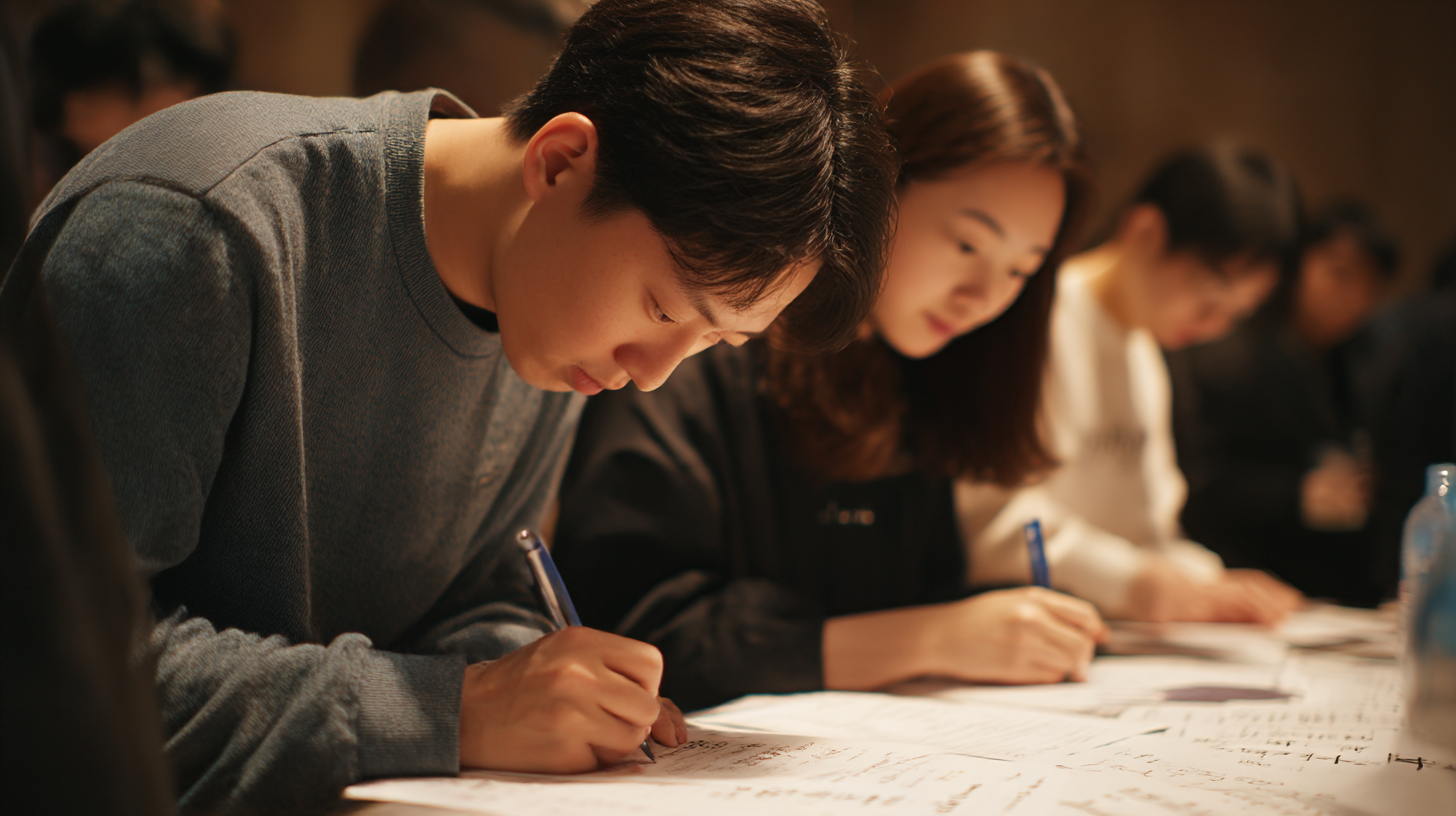
성인도 가능한 바른글씨 교정법 어릴 적에는 반듯하게 글씨를 쓰라고 많이 들었지만, 성인이 된 지금도 내 글씨체가 마음에 들지 않아 고민이 되곤 해요. 특히 회사나 일상에서 손글씨를 써야 할 때, 나도 모르게 나오는 지저분한 글씨는 자신감을 떨어뜨릴 수 있어요. 하지만 너무 걱정하지 않아도 돼요!
성인도 충분히 글씨체를 교정할 수 있고, 하루 5분만 투자해도 큰 변화가 생길 수 있답니다. 지금부터 성인을 위한 바른글씨 교정법을 재미있고 알기 쉽게 소개할게요. ✍💡
이제 본격적으로 글씨체 교정의 세계로 들어가 볼까요? 다음 섹션부터는 정말 실용적인 팁이 가득하니 끝까지 따라와 주세요!
✏ 글씨 교정의 중요성과 필요성
글씨체는 단순한 필기 이상의 의미를 가지고 있어요. 누군가에게는 첫인상을 좌우하는 요소가 되기도 하고, 스스로에게는 표현력과 자존감의 일부가 될 수 있죠. 특히 업무 메모나 감사 카드, 인터뷰 현장 등에서 글씨가 남에게 보여질 때, 깨끗하고 단정한 글씨는 세련된 이미지를 줄 수 있어요.
실제로 한 취업포털의 조사에 따르면, 손글씨가 깔끔한 사람에게 긍정적인 인상을 받는다고 응답한 비율이 70%를 넘었어요. 그만큼 글씨는 무언의 커뮤니케이션 도구로 작용하는 거예요. 내 글씨체가 어지럽거나 휘갈겨진다면, 그 인상도 달라질 수 있다는 거죠.
이런 점에서 볼 때 성인에게도 글씨 교정은 충분히 의미 있어요. 어릴 적 훈련이 부족했거나, 컴퓨터에 익숙해져 손글씨가 줄어든 이들에게는 오히려 지금이 좋은 기회일 수 있어요. 글씨는 연습을 통해 얼마든지 바뀔 수 있거든요!
내가 생각했을 때 글씨 교정은 단순히 ‘예쁘게 쓰기’를 넘어서 집중력, 자존감, 표현력까지 키울 수 있는 좋은 방법 같아요. 글씨가 바뀌면 내 태도와 마음가짐도 긍정적으로 달라질 수 있어요.
📊 글씨체가 주는 첫인상 조사 결과
항목 긍정 응답률 부정 응답률 비고 깔끔한 손글씨 71% 12% 호감도 높음 흘려쓴 글씨 15% 64% 신뢰도 낮음 필기체 스타일 36% 28% 개성 표현 가능 이처럼 글씨는 단순한 기록이 아니라, 나를 표현하는 중요한 요소예요. 다음 섹션에서는 좋은 글씨를 쓰기 위한 첫걸음, ‘자세’에 대해 알아볼게요.🧘
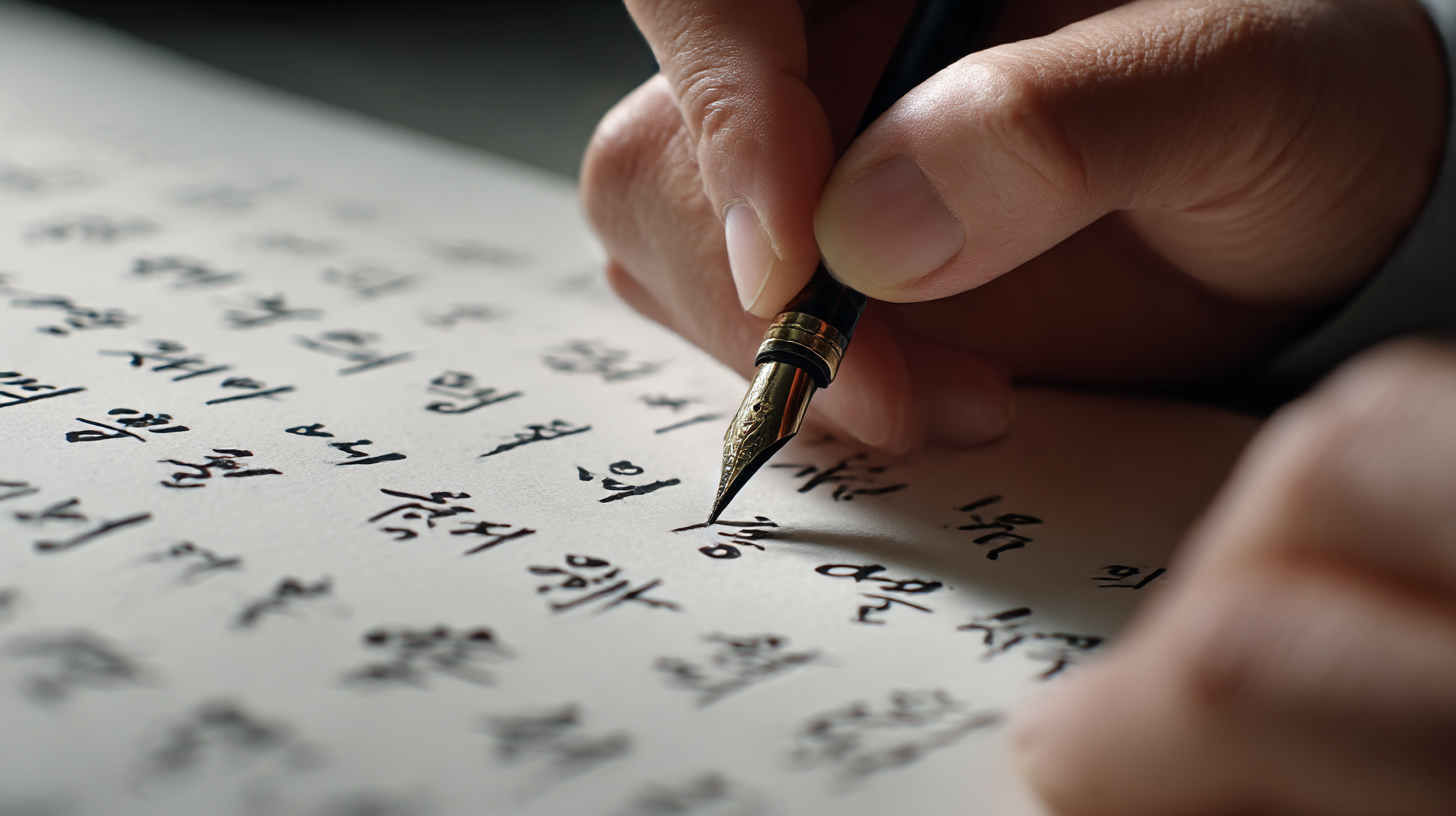
글씨 교정의 중요성과 필요성 🧘 올바른 자세가 주는 효과
글씨체를 바꾸고 싶다면 가장 먼저 바꿔야 할 건 바로 '자세'예요. 글씨는 손으로 쓰지만, 그 기반은 몸 전체의 균형에서 시작되거든요. 특히 등과 어깨가 구부정하거나, 고개가 너무 숙여진 상태에서는 손끝의 움직임도 자연스럽지 않게 돼요.
좋은 자세는 글씨를 또렷하게 만들 뿐 아니라, 오래 써도 손에 무리가 덜 가게 도와줘요. 책상과 의자 높이가 잘 맞지 않으면 글씨체가 삐뚤어지고, 손목이나 팔에도 피로가 쉽게 쌓이게 되죠. 그래서 ‘앉는 법’부터 제대로 익히는 게 중요해요!
올바른 자세의 핵심은 3가지예요: 허리를 곧게 펴고, 팔꿈치는 책상에 붙이며, 눈과 노트의 거리는 30cm 이상 유지하기! 간단하지만 이 기본만 잘 지켜도 글씨의 선이 훨씬 안정감 있어져요. 특히 눈과의 거리 조절은 시력 보호에도 좋답니다. 👀
몸의 중심을 잡는 연습은 명상이나 요가에서도 중요하게 여겨지죠. 글씨체 교정에서도 자세가 바로 중심축이 되어줘요. 중심이 흔들리면 글씨도 흔들리는 법이니까요. 글씨 교정을 위한 첫걸음은 바른 자세부터 시작해요! 💺
📋 바른 글씨 자세 체크리스트
자세 항목 좋은 습관 피해야 할 습관 허리 자세 의자 등받이에 바르게 기대기 허리를 앞으로 구부정하게 굽힘 팔의 위치 팔꿈치를 책상에 고정 팔을 공중에 띄운 채 쓰기 시선 거리 눈과 종이 사이 30~35cm 고개를 너무 숙이거나 가까이 붙이기 좋은 글씨를 위한 몸의 준비가 끝났다면, 이제 실전으로 들어가야겠죠? 다음 섹션에서는 하루 5분만 투자해도 되는 실천 가능한 글씨 교정법을 알려줄게요! 🕐✍
🕐 하루 5분, 실천 가능한 교정법
글씨 교정이라고 하면 거창한 연습장을 사고 매일 몇 시간씩 해야 할 것 같지만, 사실 매일 딱 5분만 꾸준히 해도 놀라운 변화가 생겨요. 중요한 건 '짧고 정확하게', 그리고 '지속적으로' 하는 거예요. 이건 글씨뿐만 아니라 모든 습관 형성의 기본이기도 하죠.
우선 추천하고 싶은 첫 번째 방법은 ‘베이스라인 연습’이에요. 이는 글씨를 쓸 때 기준이 되는 선에 맞춰 일정한 크기와 간격으로 쓰는 훈련이죠. 낙서처럼 쓰던 글씨도 베이스라인을 의식하며 쓰면 한결 정돈된 느낌을 줄 수 있어요.
두 번째는 ‘느리게 쓰기’예요. 평소보다 두 배 느린 속도로 한 자 한 자를 의식하면서 써보세요. 처음엔 답답할 수 있지만, 이 과정에서 글자의 균형과 모양을 자연스럽게 익힐 수 있어요. 특히 자주 틀리는 글자나 모양이 이상한 글자는 반복 연습이 효과적이죠.
세 번째는 ‘거울 보고 쓰기’예요. 이건 거울에 비친 글씨를 보면서 구조적 불균형을 확인하고, 교정하는 훈련이에요. 약간 생소하게 느껴질 수 있지만, 의외로 효과가 좋아서 필기체 연습에도 많이 활용된답니다. 🎯
🗂 하루 5분 훈련 루틴 예시
시간 훈련 내용 목표 효과 1분 손 풀기, 스트레칭 손목 유연성 확보 2분 베이스라인 연습 글자 정렬과 균형 1분 느리게 필기 자세 교정 및 집중력 향상 1분 거울 연습 글씨체 자가 점검 하루 5분만 투자하면 부담도 없고, 오히려 짧은 시간이라 더 집중해서 할 수 있어요. 중요한 건 “내일도, 모레도 하자”는 마음가짐이에요. 이제 글씨 교정을 도와주는 도구들에 대해 소개할게요. ✏
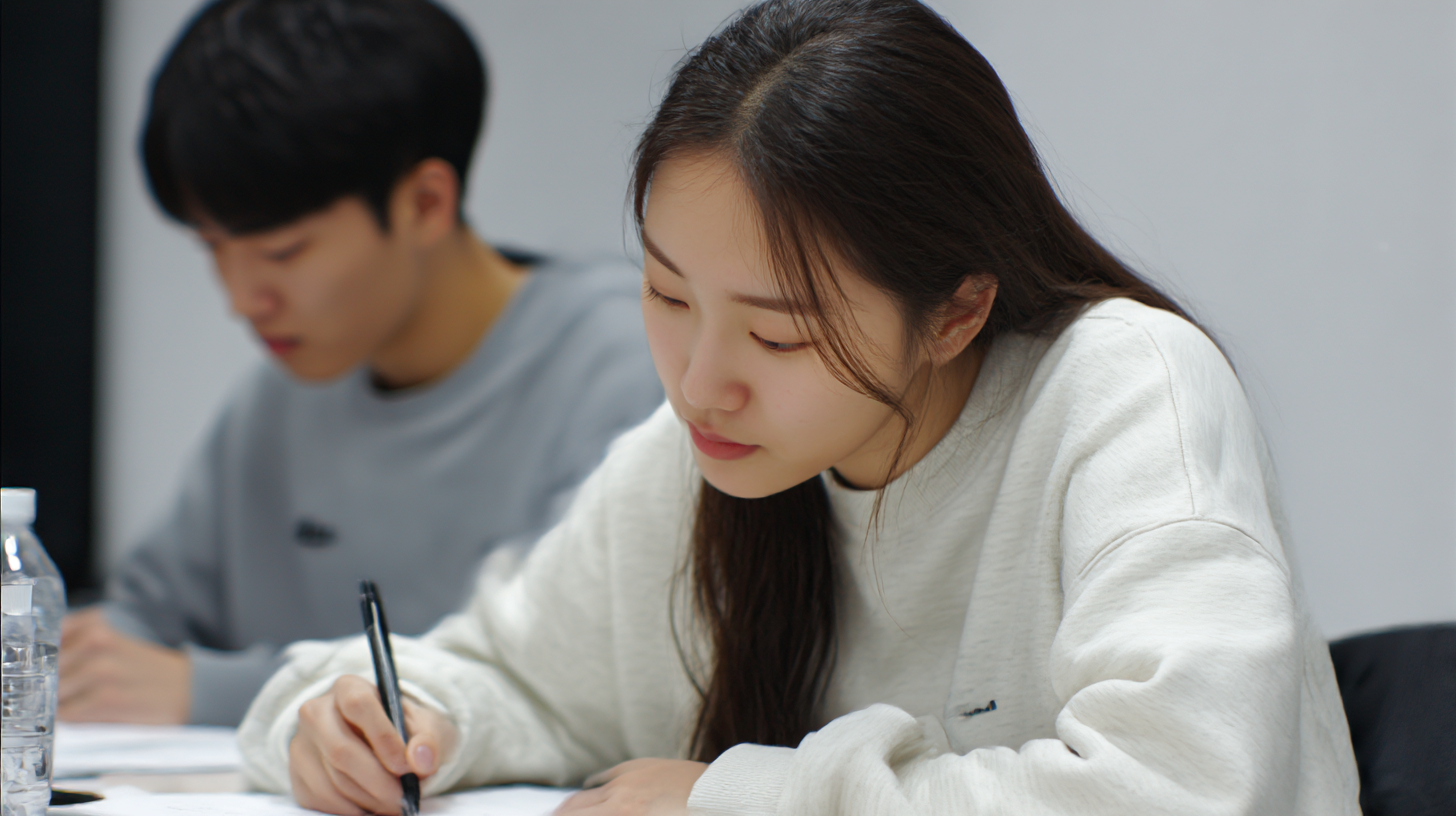
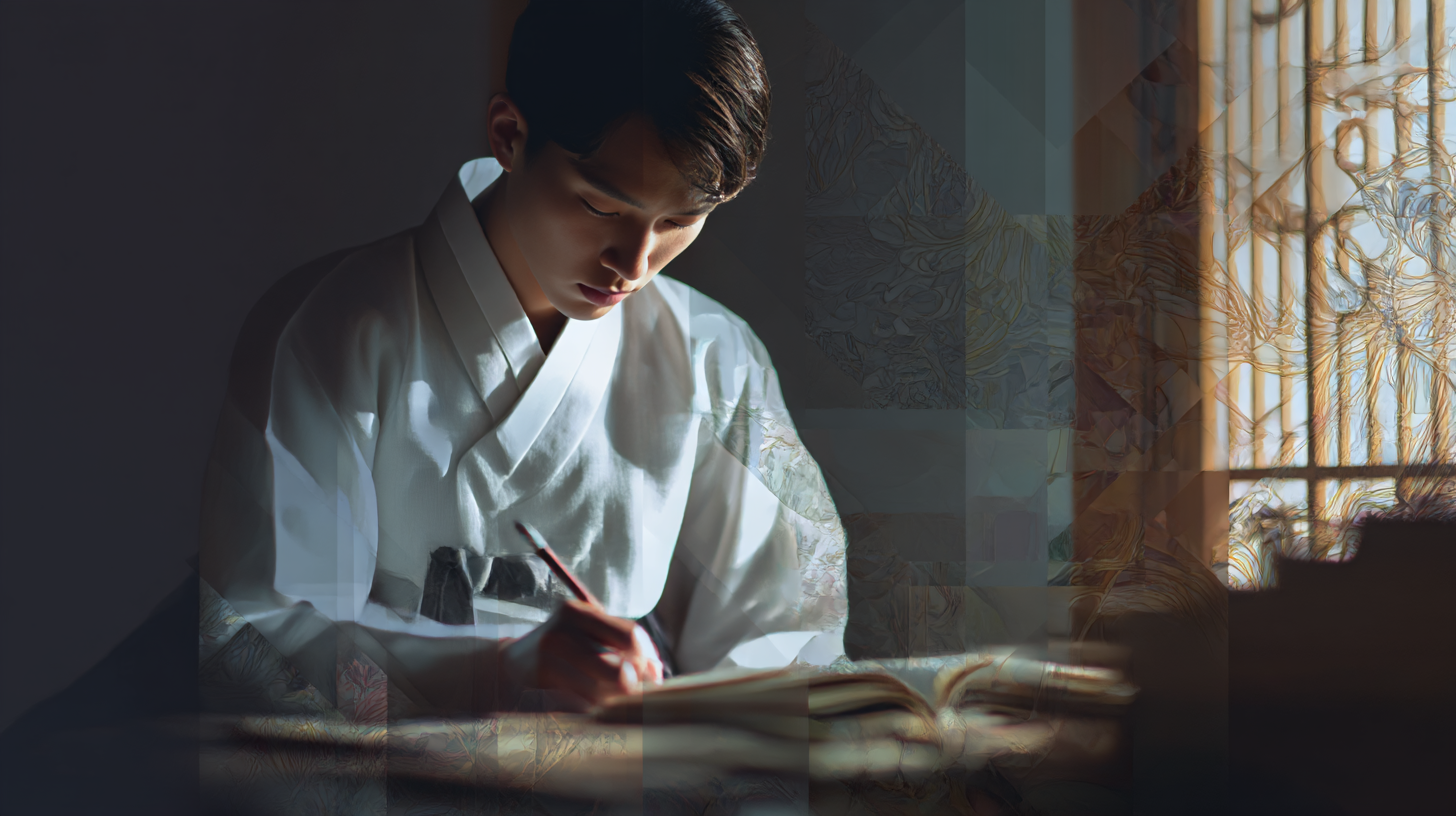
하루 5분, 실천 가능한 교정법 🖊 도움이 되는 필기 도구 추천
글씨체 교정에서 필기 도구는 생각보다 큰 역할을 해요. 손에 잘 맞지 않는 펜이나 종이를 쓰면 필기감이 불편하고, 그만큼 글씨도 부정확해지거든요. 그래서 연습할 땐 내 손에 꼭 맞는 도구를 고르는 게 아주 중요해요.
먼저 펜부터 이야기해 볼게요. 초보자라면 잉크 흐름이 일정한 젤펜이 좋아요. 너무 미끄럽지 않으면서도 부드럽게 써지기 때문에 선의 굵기를 조절하기 쉽고, 힘 조절도 자연스러워요. 샤프나 볼펜도 괜찮지만, 펜촉이 얇아 지나치게 긴장되면 손이 떨리기 쉬워요.
노트도 중요해요. 줄이 없는 백지보다는 연습용 유선지, 특히 ‘세로 8mm 라인’이 있는 공책이 좋아요. 이 줄 간격은 한글의 구조에 맞춰져 있어서 정자체 연습에 최적화되어 있답니다. 그리고 종이 재질도 부드럽고 번짐 없는 것이 좋아요.
마지막으로, 펜을 잡는 ‘그립 보조기’도 추천해요. 펜을 바르게 잡는 훈련을 도와주기 때문에 손가락 위치가 안정되면서 글씨도 더 정돈돼 보여요. 특히 성인 중에도 펜을 잘못 잡는 경우가 많아, 초기엔 이런 도구들이 큰 도움이 돼요.
🖍 글씨체 교정에 추천하는 도구들
도구명 특징 추천 이유 제브라 사라사 젤펜 잉크 흐름이 부드럽고 고르게 나옴 초보자도 손쉽게 정자체 가능 8mm 유선 노트 가이드라인이 있어 글씨 정렬에 도움 형태 안정성 향상 실리콘 그립 보조기 펜 잡는 위치 교정 가능 올바른 필기 습관 형성에 효과적 좋은 도구는 연습을 더 쉽게, 더 즐겁게 만들어줘요. 부담 없이 쓰기 좋고 꾸준히 연습할 수 있는 도구들을 잘 선택해서 시작해 보세요. 다음 섹션에서는 이 연습을 습관으로 만드는 방법을 알려줄게요! 🗓
📆 꾸준함을 위한 습관 만들기
좋은 글씨체를 만드는 핵심은 바로 ‘꾸준함’이에요. 하루 5분이 아무리 짧아도, 그 5분이 매일 이어진다면 글씨는 확실히 달라져요. 실제로 많은 사람들이 ‘하루 5분 루틴’을 30일만 실천해도 눈에 띄는 차이를 경험한다고 해요.
습관을 만드는 가장 쉬운 방법은 ‘정해진 시간에 같은 장소에서 하기’예요. 예를 들어, 아침에 커피 마시기 전에 5분간 연습하거나, 자기 전 5분을 정자체 쓰기로 정해보세요. 반복은 뇌에 ‘이건 일상이다’라는 신호를 주게 되죠.
또한 눈에 보이는 변화가 있어야 동기부여가 되니까, 연습한 글씨를 매일 사진으로 남겨보세요. 일주일, 한 달 뒤 비교해보면 스스로도 놀라게 될 거예요. SNS에 올려 다른 사람들과 공유하는 것도 좋고요. 🔄📸
그리고 작은 성공을 자주 느끼는 것도 중요해요. 예를 들어, 한 줄만 예쁘게 쓰기, 10분 동안 집중하기 같은 미션을 달성했을 때 스스로에게 ‘잘했어!’라고 말해주는 거죠. 습관은 이런 긍정적 피드백과 함께 자라나요. 🌱
📈 글씨 연습 꾸준함 실천법
방법 내용 효과 시간 고정 하루 중 정해진 시간에 연습 루틴 형성 쉬움 시각화 전후 비교 사진 기록 진행 상황 파악 보상 시스템 작은 목표 후 보상 동기부여 상승 이제 어느 정도 글씨 교정의 방법과 도구, 그리고 꾸준함까지 익혔다면… 실제로 이 방법을 실천해서 바뀐 사람들이 있을까요? 물론이죠! 다음 섹션에서는 직접 교정에 성공한 분들의 후기를 소개할게요. 💬
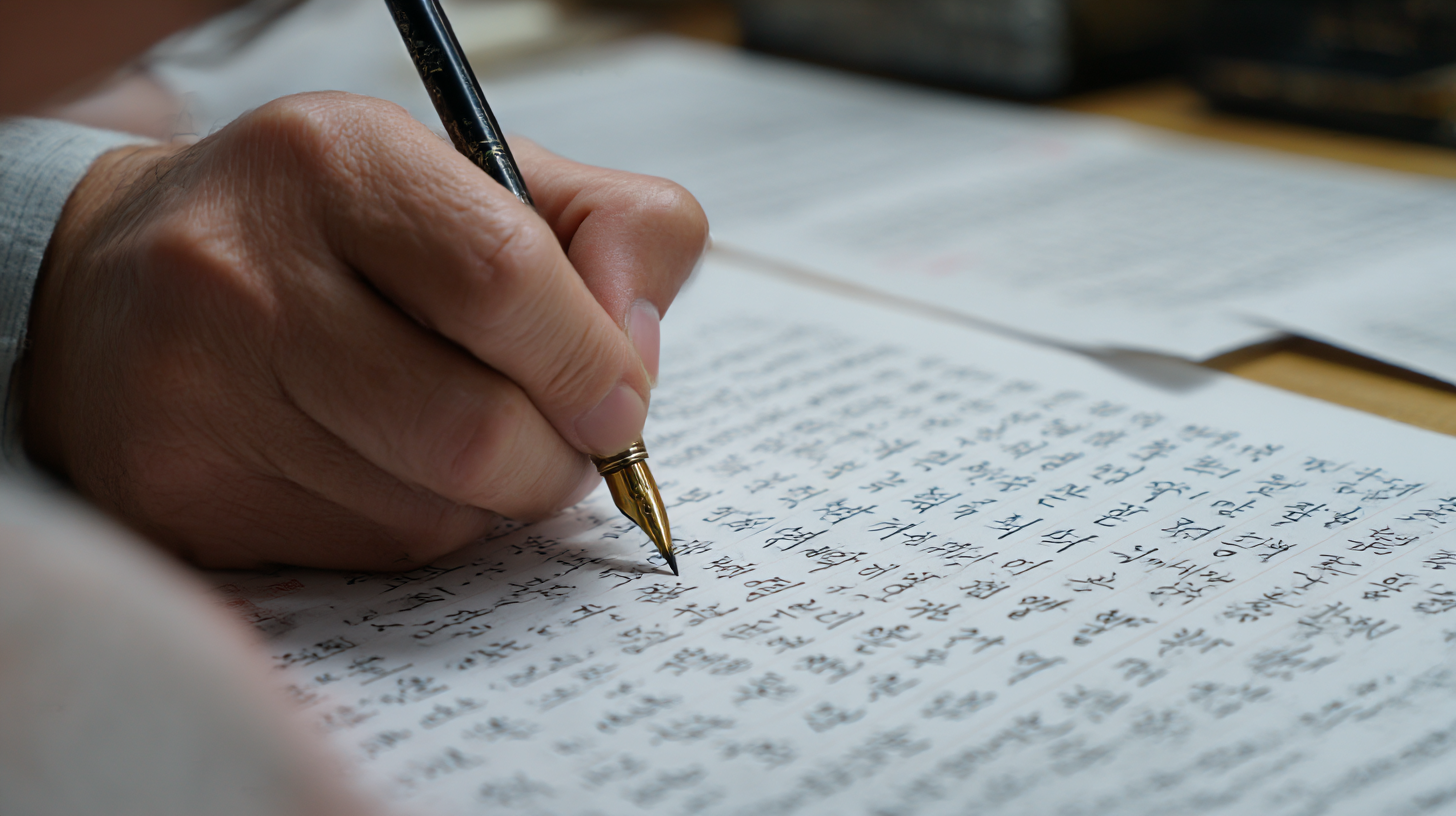
꾸준함을 위한 습관 만들기 💬 성공한 사례와 후기 소개
하루 5분 글씨 연습이 진짜 효과가 있을까? 실제로 많은 성인들이 단기간에 눈에 띄는 변화를 경험했어요. 여기 소개하는 후기는 그저 이론이 아니라, 매일 조금씩 꾸준히 연습한 ‘진짜 사람들’의 이야기예요.
첫 번째 후기는 30대 직장인 민정 씨의 이야기예요. 민정 씨는 회의록을 손글씨로 정리할 일이 많은데, 글씨체가 알아보기 어려워 동료들에게 종종 지적을 받았다고 해요. 그래서 시작한 하루 5분 정자체 연습, 두 달 후 민정 씨는 글씨가 또렷하고 균형 있게 바뀌었고, 이제는 동료들이 필기 노트를 칭찬할 정도예요!
두 번째는 대학생 정훈 씨예요. 정훈 씨는 졸업 논문 준비 중 자필 메모를 자주 쓰는데, 글씨가 너무 흐려서 본인도 알아보기 힘들었다고 해요. ‘베이스라인 연습’과 ‘거울 보기 연습’을 병행하면서, 점차 글씨에 힘이 생기고 곡선도 부드러워졌대요. 그는 “내 글씨에 자신감이 생겼다”고 해요. 💪
세 번째는 은퇴 후 손주들에게 편지를 자주 쓰는 정현 할아버지의 이야기예요. 자녀와 손주들에게 ‘읽기 편한 편지’를 주고 싶어 시작한 글씨 연습이었는데, 이젠 손주들이 “할아버지 글씨가 너무 예뻐요”라고 말한대요. 가족 간 소통의 질도 함께 높아진 거죠. 🧓👨👧👦
Q4. 필기도구는 꼭 좋은 걸 써야 하나요?
A4. 꼭 비싼 것이어야 하는 건 아니지만, 손에 잘 맞고 필기감이 좋은 도구를 쓰면 연습 효율이 높아져요. 추천 도구는 앞에서 소개했어요!
Q5. 글씨체가 일정하지 않고 흔들리는 이유는 뭔가요?
A5. 대부분 자세가 흐트러지거나 손에 너무 힘이 들어가서 그래요. 바른 자세와 ‘느리게 쓰기’를 병행해보세요. 균형 있는 글씨로 바뀔 거예요.
Q6. 교정 효과가 나타나기까지 얼마나 걸릴까요?
A6. 개인차는 있지만, 보통 2~4주 정도면 눈에 띄는 변화가 시작돼요. 1달만 꾸준히 해보세요. 이전의 글씨가 아쉽게 느껴질 거예요.
Q7. 왼손잡이도 글씨체 교정이 가능한가요?
A7. 당연히 가능해요! 왼손잡이용 펜이나 그립 보조도구가 있으니 그런 도구들을 활용해서 시작하면 좋아요.
Q8. 필체 교정 앱도 도움이 될까요?
A8. 네, 요즘은 디지털 글씨체 교정 앱도 꽤 유용해요. 다만 손글씨 감각을 익히기 위해 종이 연습과 병행하는 걸 추천해요.